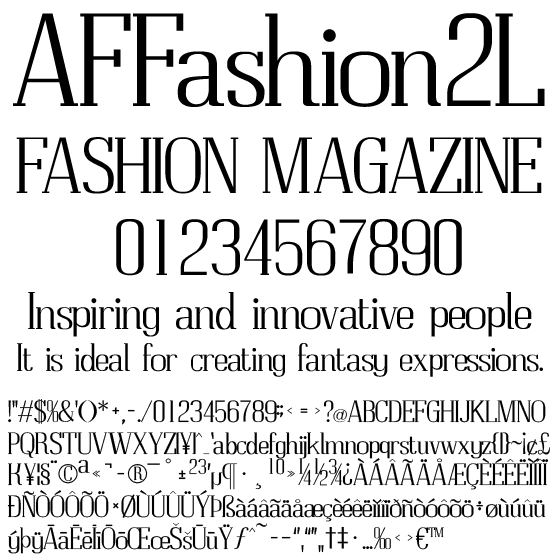
ファッション系 欧文ォント AFFashion2L
AFFashion2L
狭いサイドベアリングに強カーニングでファッション系に最適なライトウェイト欧文フォントです。ドキュメント、写真、動画テロップ、WebPage などにいかがでしょうか。パンフレット、リーフレット、フライヤー、ファッション系コンテンツに使えるフォントです。日本のローマ字表記で使われる訓令式やヘボン式で扱う Ô や Ō を収録、人名地名へのアプローチもリアルです。